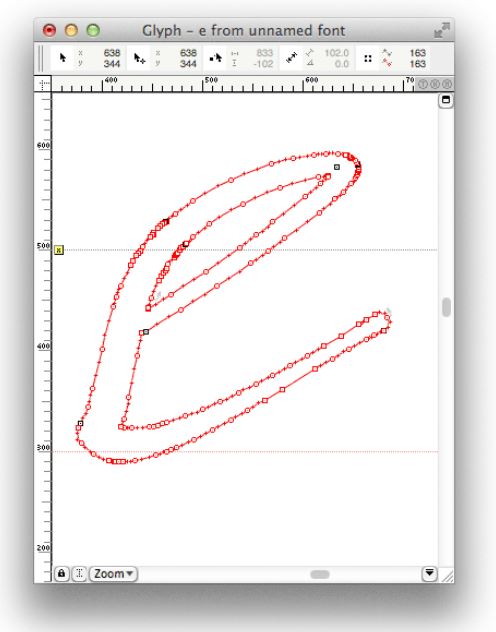
Digitalisieren handgezeichnete Schrift
Ich habe eine Frage zu der Digitalisierung von handgezeichnete Schriftarten. Ich habe mich damit beschäftigt, einige von mir gezeichnete Buchstaben und Icons zum Font zu machen. Dabei habe ich bisher immer so gearbeitet.
- Scan in hoher Auflösung (600-1200 dpi), graustufen oder bitmap.
- Aufarbeiten in Photoshop
- "Trace" in Illustrator, danach leicht vereinfachen der Kontur (97-99%)
- Umsetzung nach Glyphs Mini
Die letzte Schritte sind problematisch da bei der Trace meistens viel zu viele Nodes bleiben, oder zuviel verloren geht vom Original. Auch die Umsetzung nach Glyphs Mini ist nicht 1=1 und produziert ggf. noch mehr Problemen. Ich habe auch versucht direkt in Glyphs die Vorlage nachzuzeichnen. Das funktioniert ziemlich gut, nur ist es schwer den handgezeichnen Character zu behalten.
Habt ihr Tipps für mich wie ich es besser machen kann??
Auto-Trace ist immer problematisch. Für gute Fonts sollte man die Kontur immer selbst nachzeichnen. Von Illustrator zu Glyphs sollte man eigentlich ohne Qualitätsverluste kommen. Da gäbe es zwei Möglichkeiten:
1. Du legst das Fontraster schon in Illustrator an und lässt alle Punkte an diesem Raster ausrichten. Dann kommt es beim Wechsel zum Fonteditor zu keinen Rundungsfehlern.
2. Du schaltest in Glyphs das Raster ab. (Ich hoffe mal das ist keine Funktion, die nur die Pro-Version hat.) Dann erhältst du in Glyphs Fließkomma-Koordinaten, aber damit kann das Programm im Gegensatz zu den meisten anderen Fonteditoren umgehen.
ja, ich glaube auch das nachzeichnen die brauchbarste Ergebnisse bringt. Nur habe dann das Problem das "handgemachte" der Schriftart zu behalten. Gibt es da noch Tipps?
Ja, ich mache das imm er so, dass ich das aufgearbeitete Scanbild im Vektorgrafik-Programm (ich nutze CorelDRAW, das ist aber egal) auf eine andere Ebene unter die Zeichenebene packe, und diese dann vor der Bearbeitung schütze. Hierdurch verschiebe ich nicht versehentlich die Vorlage.
Dann zeichne ich die Kurven derart nach, dass ich gezielt die Knoten da setze, wo sich die Krümmungsrichtung der Kurve ändert, sowie an den Extremen der Kurve in der horizontalen und vertikalen. Ich zeichne dabei zunächst gerade Liniensegmente, die ich, bin ich um die Kontur herum in gekrümmte Kurven umstelle (sofern es eben auch in der Vorlage keine Geraden sind), und dann einzeln genau an die Vorlage heran ziehe. Anschließen werden die Knoten, die nicht wirklich eine Ecke bilden geglättet und die Ankerpunkte der Extrem-Knoten genau waagerecht und senkrecht ausgerichtet.
Ich glaube auch das eine Methode wie du sie beschreibst wahrscheinlich am besten und zuverlässigsten ist. Ich benutze Illustrator, aber komme mit die Zeichenwerkzeuge von Glyphs Mini besser zurecht. Da hat man aber leider nicht so viel möglichkeiten um ein Hintergrundbild zu verschieben und passend zu machen. Ich werde beide Möglichkeiten mal versuchen.
Danke Sebastian, mir ist diese Artikel auch schon aufgefallen. Es hat mich motiviert, aber wenn ich die Bilder anschaue, meine ich das hier die Konturen auch nicht optimal gezeichnet sind, vor allem nachdem man die Linien konvertiert in Flächen. Natürlich sind die Linien mit unterschiedliche Breiten für Schreibschriften sehr praktisch, aber wenn diese in so viele Nodes umgesetzt werden, muß man glaub ich doch ziemlich viel nacharbeiten. Oder was ist ihre Meinung dazu?
Wenn ich so etwas sehe, und das dann nicht schon in der Vektorgrafik aufgeräumt wird, ist das für mich schon eine mittlere Katastrophe. denn bei so vielen Knoten wird die Kontur im Font fast zwangsläufig zur Zick-Zack-Kurve, die dann auch die Bereinigungs-Funktion des Font-Editors nicht mehr glatt bekommt.
Überhaupt erzeugt die gewählte Methode gleich mehrfach ungewünschte und ungünstige Knoten, die viel Nacharbeit erfordern. schon dieses freihändige Nachziehen der Buchstaben-Mittellinie erzeugt erst einmal viele, zufällihge Knoten, die mühevoll retuschiert wurden, um dfann durch dir Strichstärken-Methode wieder zu diesem schlimmen Ergebnis führen.
Ich glaube sehr, dass ich mit meiner Methode erheblich schneller zu einem genaueren Ergebnis komme.
Das habe ich mir auch gedacht! Als Vectorzeichnung ist das vielleicht OK, aber als Font nicht. Diese relativ einfache Kurve muß doch mit wesentlich weniger Knotenpunkte zu machen sein, was die wiedergabe der Schrift warscheinlich auch verbessert.
Um eine Lanze für Harald zu brechen, also den Urheber des Sigmund-Freud-Fonts: musste auch ziemlich stutzen, als ich die Unmengen an »Knoten« (mein Gott, kann man dafür nicht einen besseren Ausdruck verwenden, Stützpunkte zum Beispiel ;-) Extrem-Stützpunkte!) in einer ziemlich frühen Form des Fonts sah, glaubte aber dies wäre nicht die Endfassung. Der „Grunge-Effekt“ der Übersetzung von Linien zu Flächen in Illustrator kommt der Handschrift von Sigmund, dem alten Kokser, allerdings zugute, möchte ich noch bemerken. Eine »saubere« Digitalisierung wär vielleicht sogar fehl am Platz gewesen – technisch scheints ja dennoch zu funktionieren (vor ein paar Jahren noch wären an so etwas vermutlich alle Ausgabegeräte in die Knie gegangen).
Nun ja, bei meiner Erika Ormig war das getracete auch nur ein Zwischenschritt. auch da ist nicht jeder digitale Krakel drin geblieben, und die Konturen gründlich noch mal vobn Hand aufgeschönt. So gleich von Autitrace geht das bei mit nicht durch, das ist mit - selbst von Vektor Magic, das ich mla probiert habe (man hat ja 2 Freischüsse) selbst bei einer recht guten Vorlage einfach zu grausam.